February 27, 2021Bagi pelaku grafis, printing, web desain dan pecinta tipografi, font gratis terbaik itu yang dicari-cari. Font gratis saja sangat mudah ditemukan tetapi menemukan font berkualitas tinggi, menyenangkan, menarik, dan elegan adalah pekerjaan yang tidak mudah. Banyak font yang dirilis dari beberapa tahun terakhir, beberapa menjadi terkenal karena kualitasnya yang superior, beberapa gagal karena beberapa alasan.
Tetapi masih ada beberapa font yang dapat digunakan di masa yang akan datang, di posting ini kami telah mengumpulkan font-font tersebut. Font-font ini semua sangat terkenal saat ini dan tidak memiliki kesempatan untuk kehilangan daya tariknya dalam waktu dekat.
1. Amaze
Font gratis terbaik jenis kaligrafi ini hadir dalam stle Italic dan Bold.
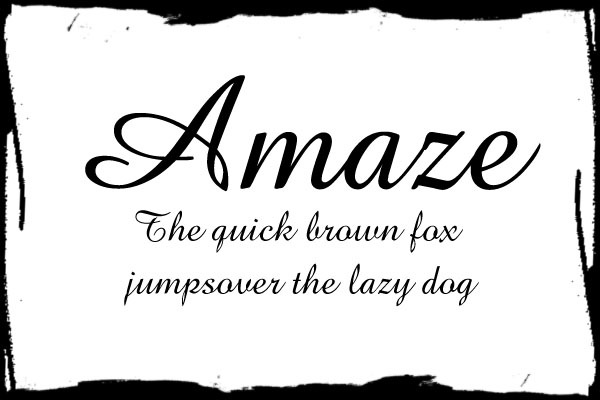
2. Avian
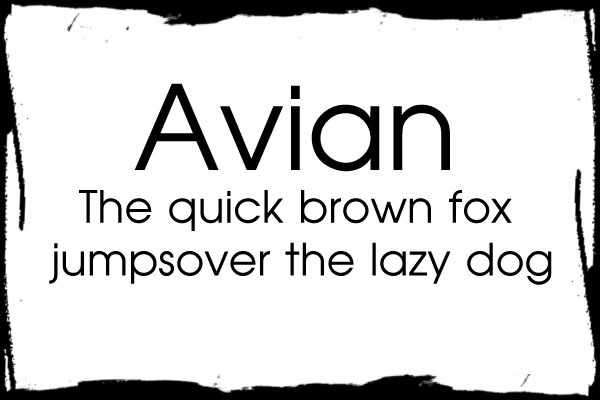
3. Bellerose
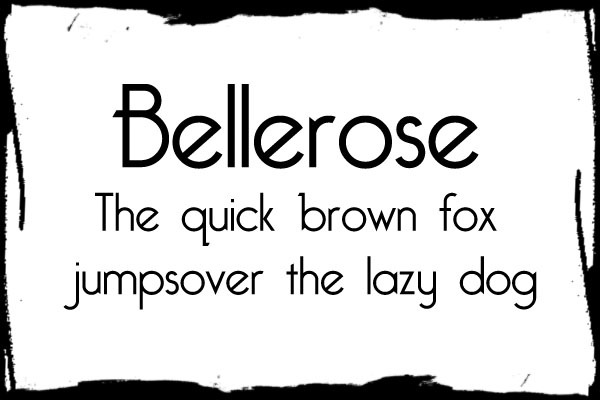
4. Birth of a Hero
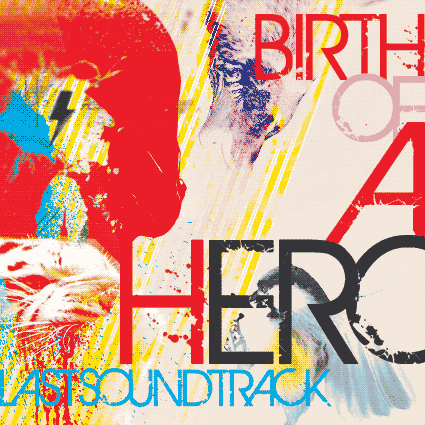
7. Champagne & Limousines
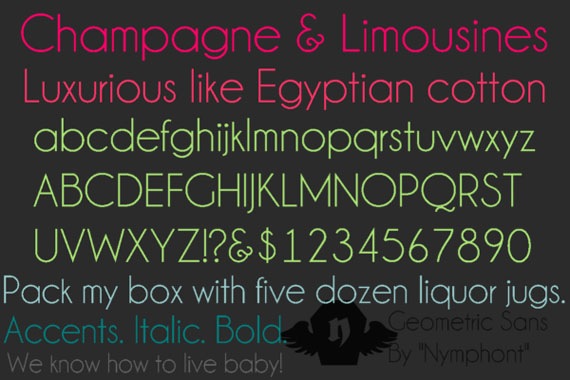
8. ChopinScript
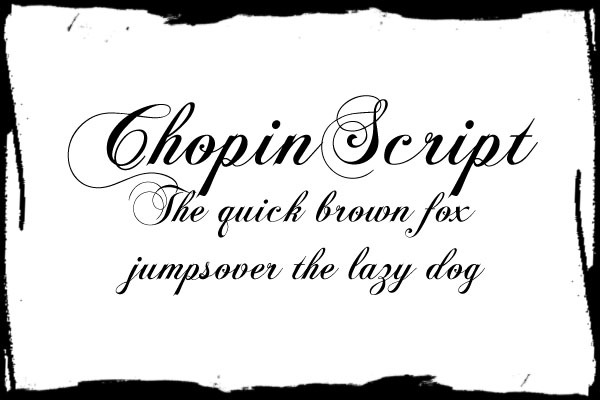
9. ClassizismAntiqua
10. Code
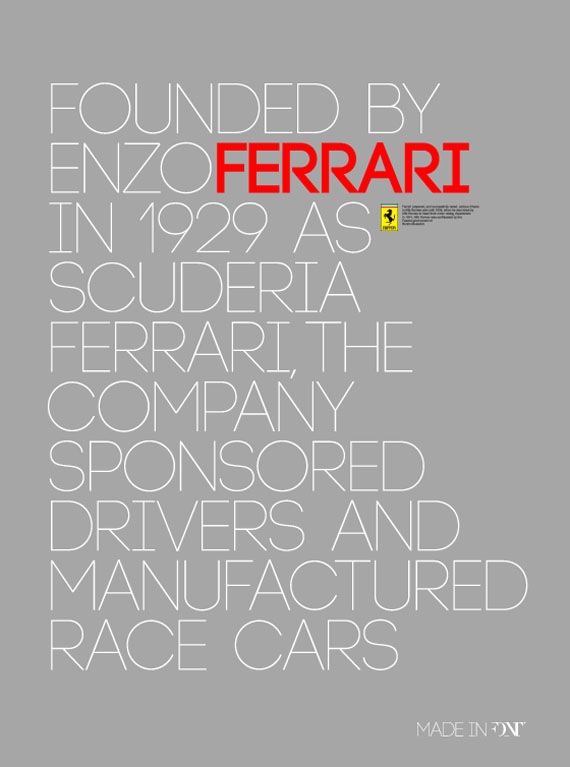
11. COM4t
12. Comfortaa